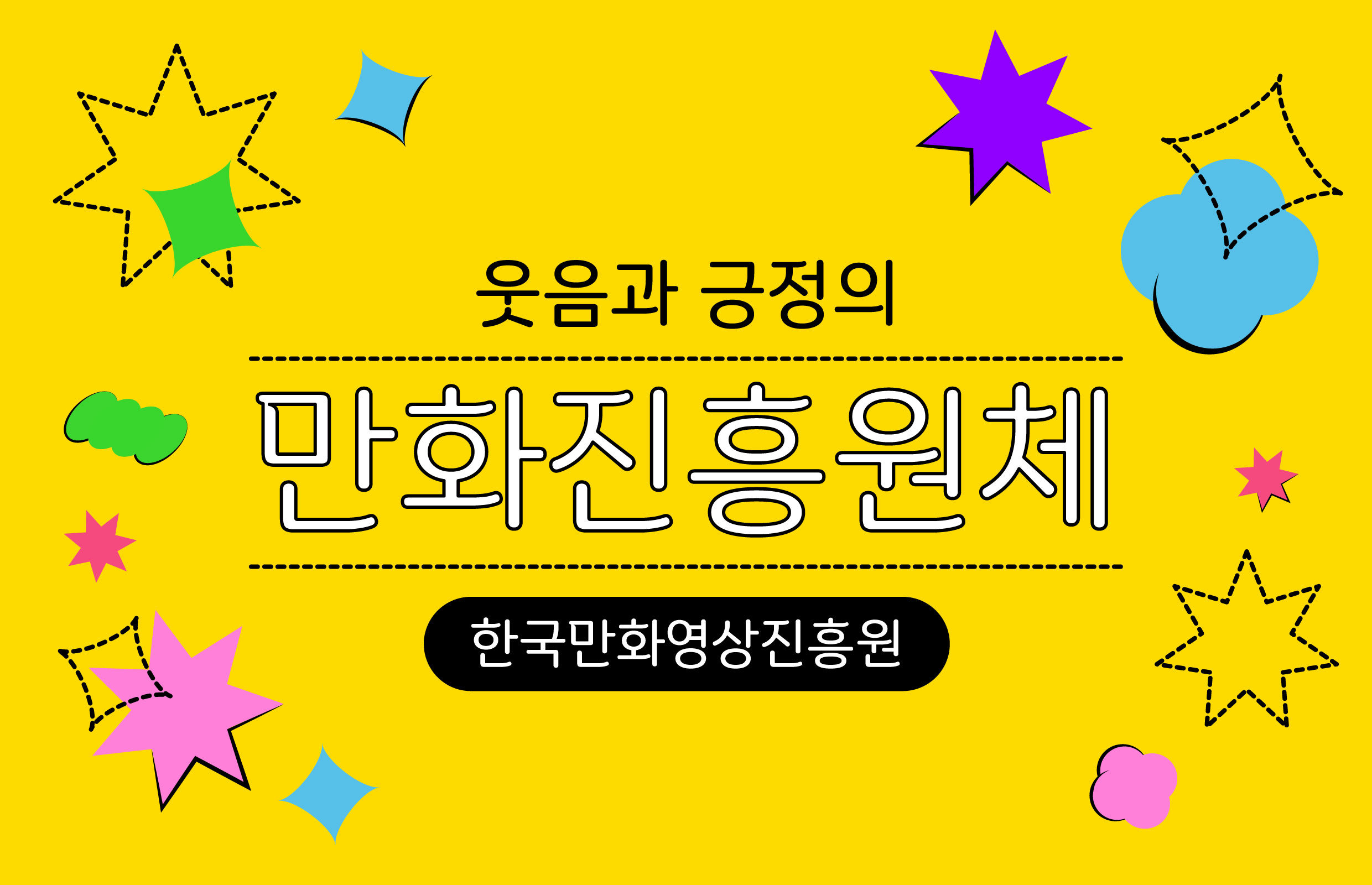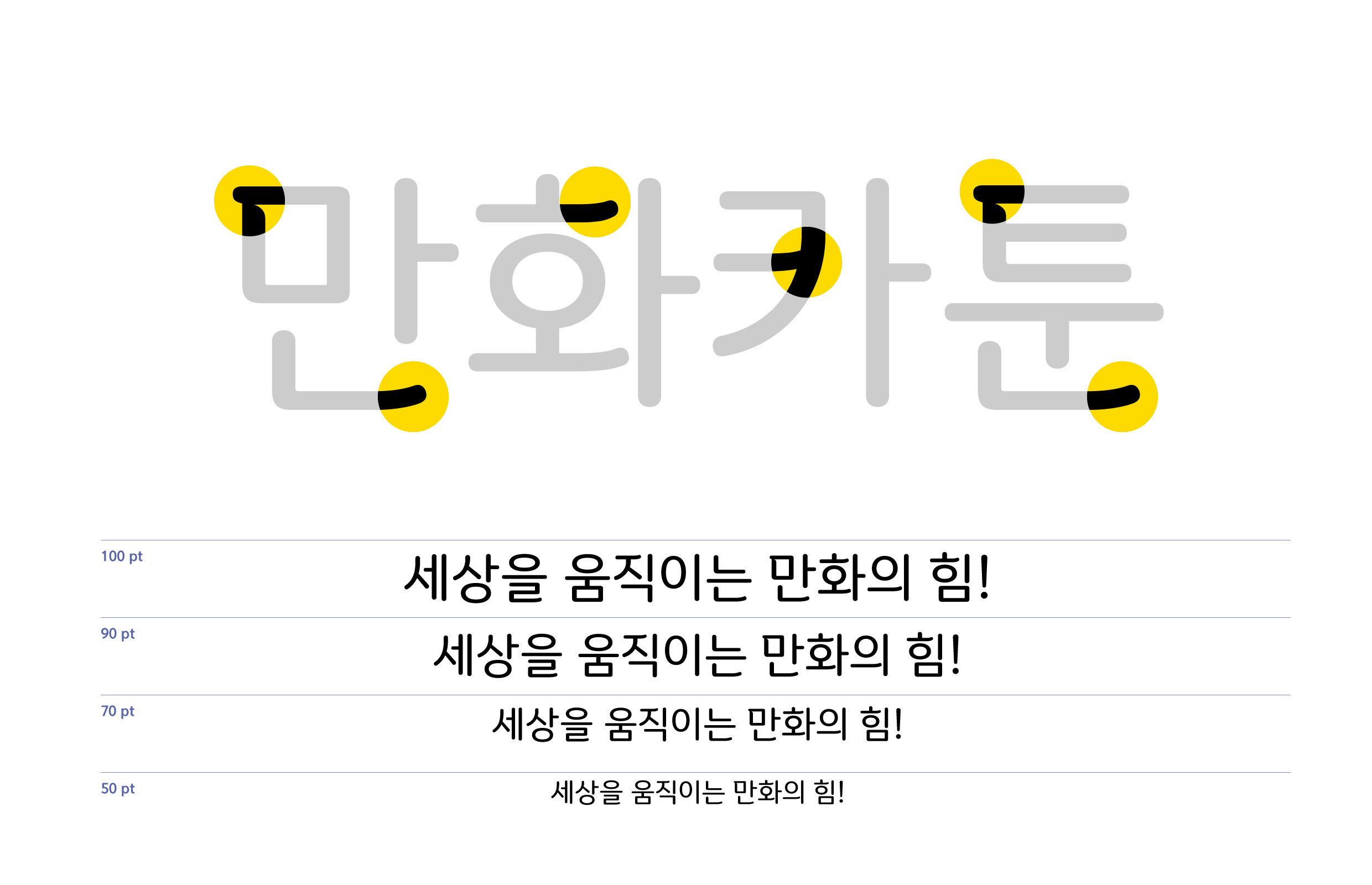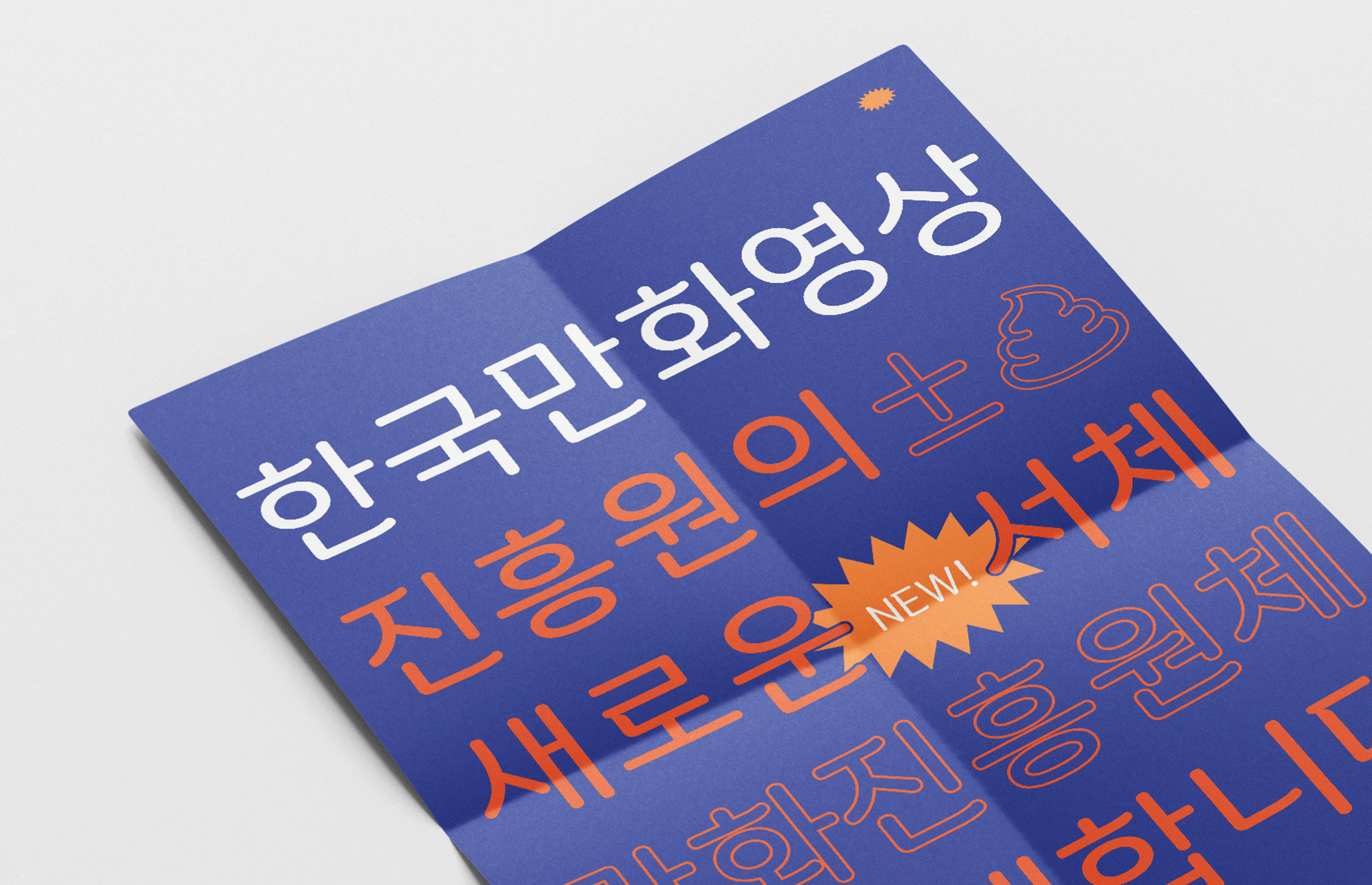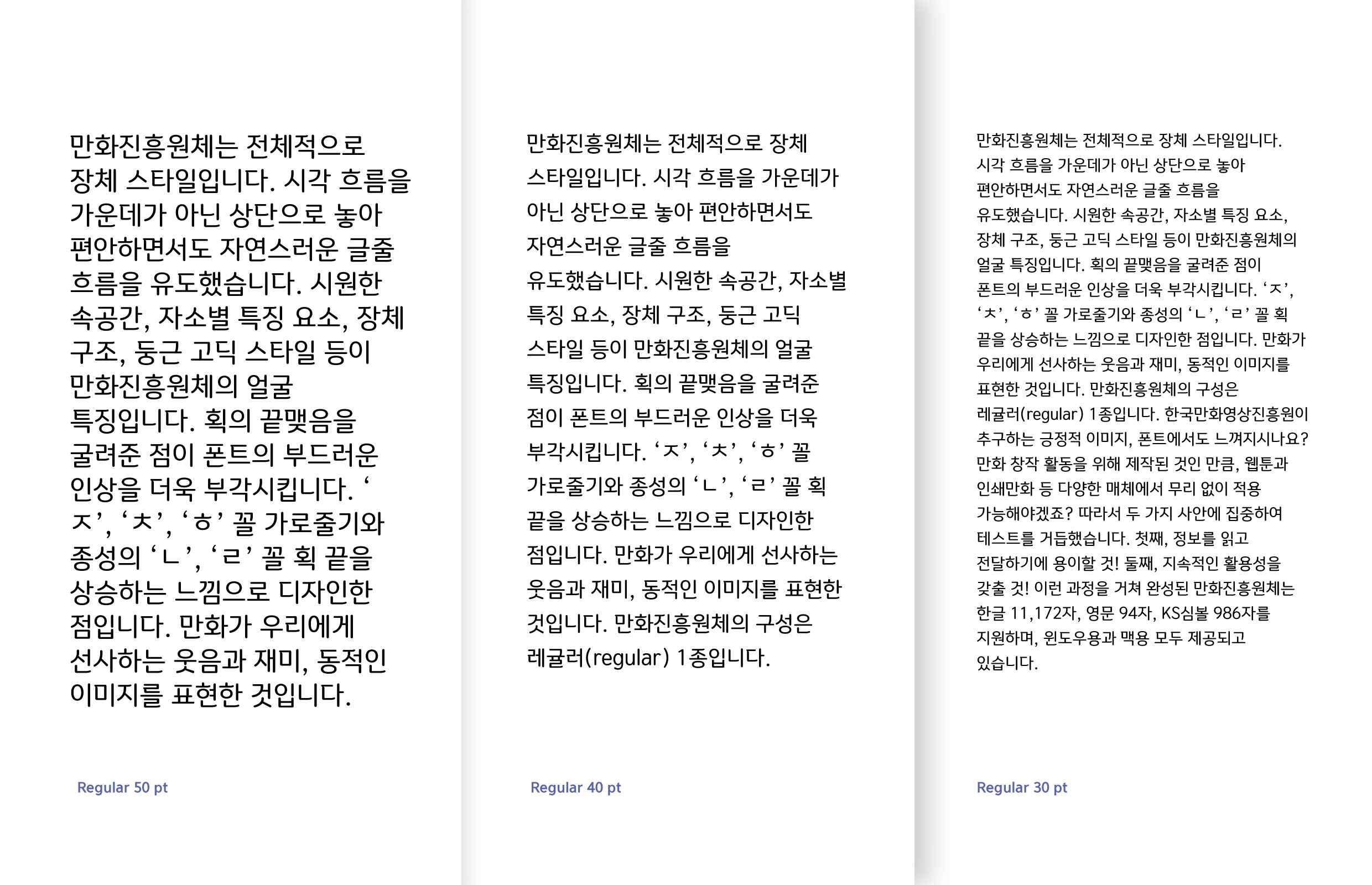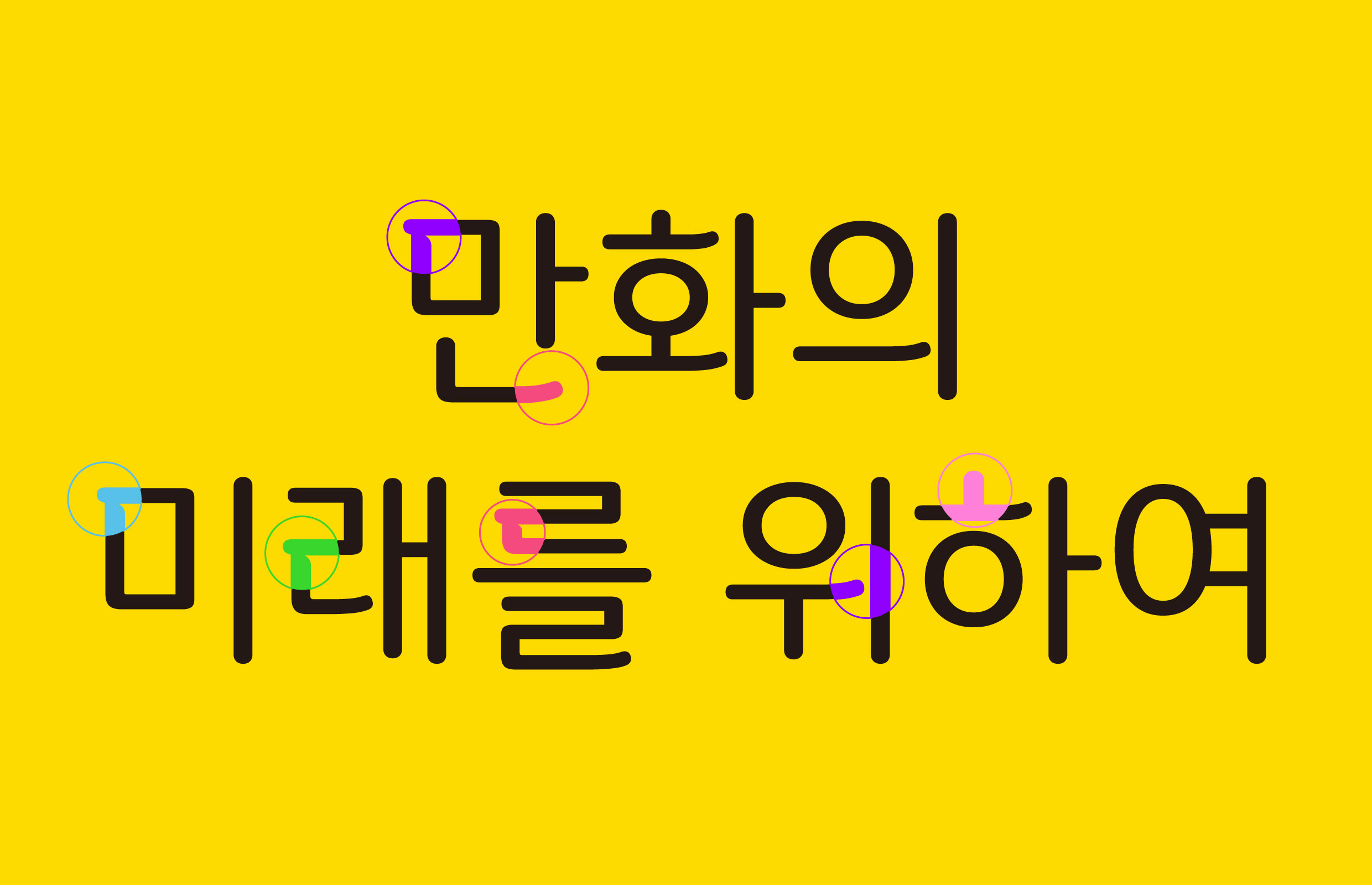
한국만화영상진흥원 [한국만화영상진흥원 전용서체]
저작권 분쟁 위험이 없는 자유로운 만화창작 환경을 만들고자 개발된 전용서체. 둥근 고딕 스타일로 획의 끝맺음을 굴려줌으로써 서체의 인상을 부드럽게 느껴지도록 제작하였으며, 미소를 짓는 입꼬리처럼 살포시 올라간 곡선 형태는 보는 사람의 입가에도 웃음이 머금어지기를 바라는 마음을 담았다.